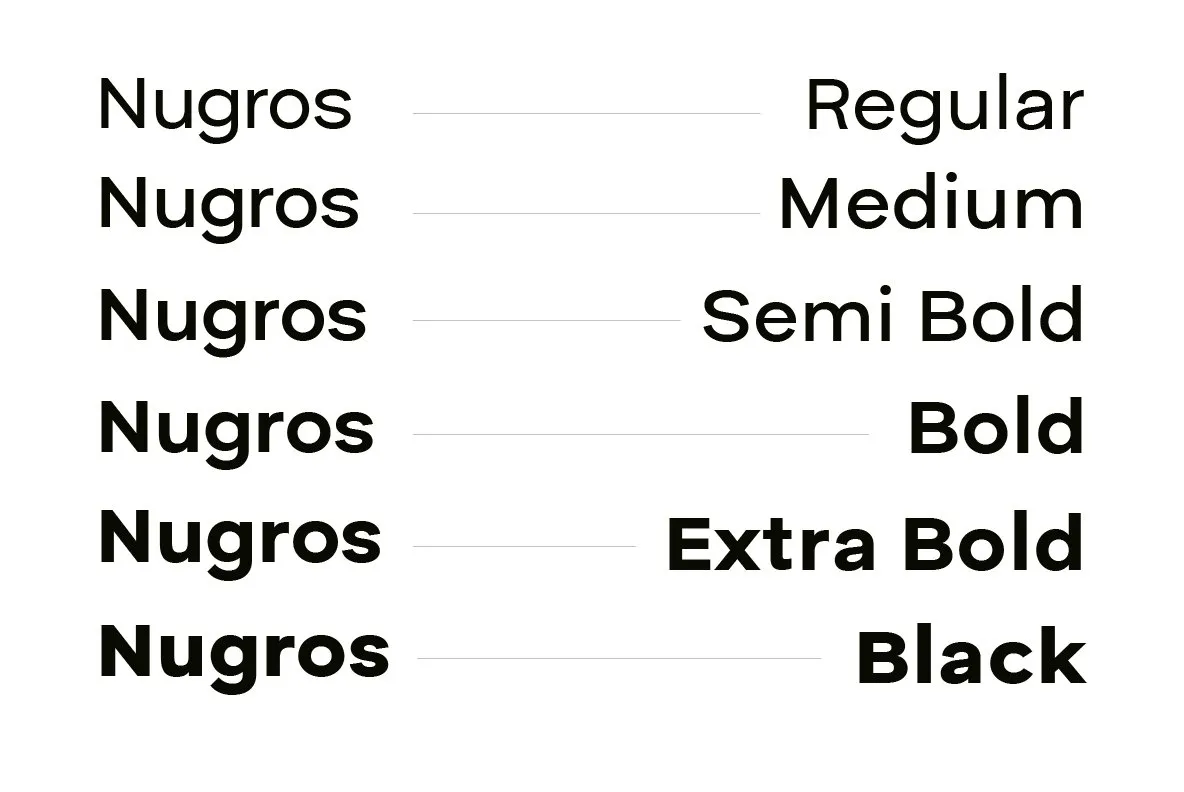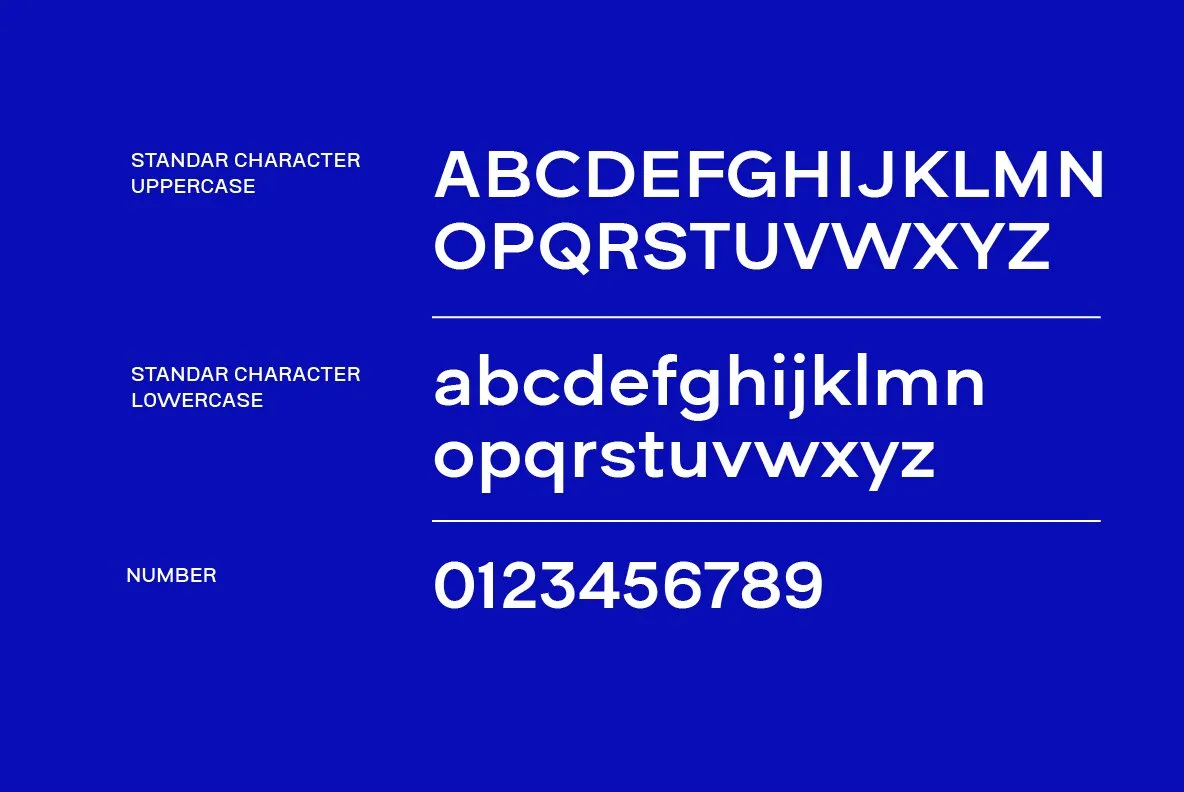
Nugros Font Sans Serif Font Family là một Kiểu chữ hiện đại, có Thiết kế đơn giản và thanh lịch. Phông chữ này Thích hợp để sử dụng trong các thiết kế trang trọng, chẳng hạn như thiết kế kỹ thuật số và thiết kế in ấn. Kiểu chữ rõ ràng, dễ đọc mang lại cảm giác chuyên nghiệp cho Thiết kế.
Nugros Sans Serif mang lại ấn tượng sang trọng và tự tin, phù hợp để sử dụng làm yếu tố chính trong thiết kế thương hiệu. Nó cũng phù hợp để sử dụng trong nhiều loại thiết kế khác nhau vì tính linh hoạt của nó.